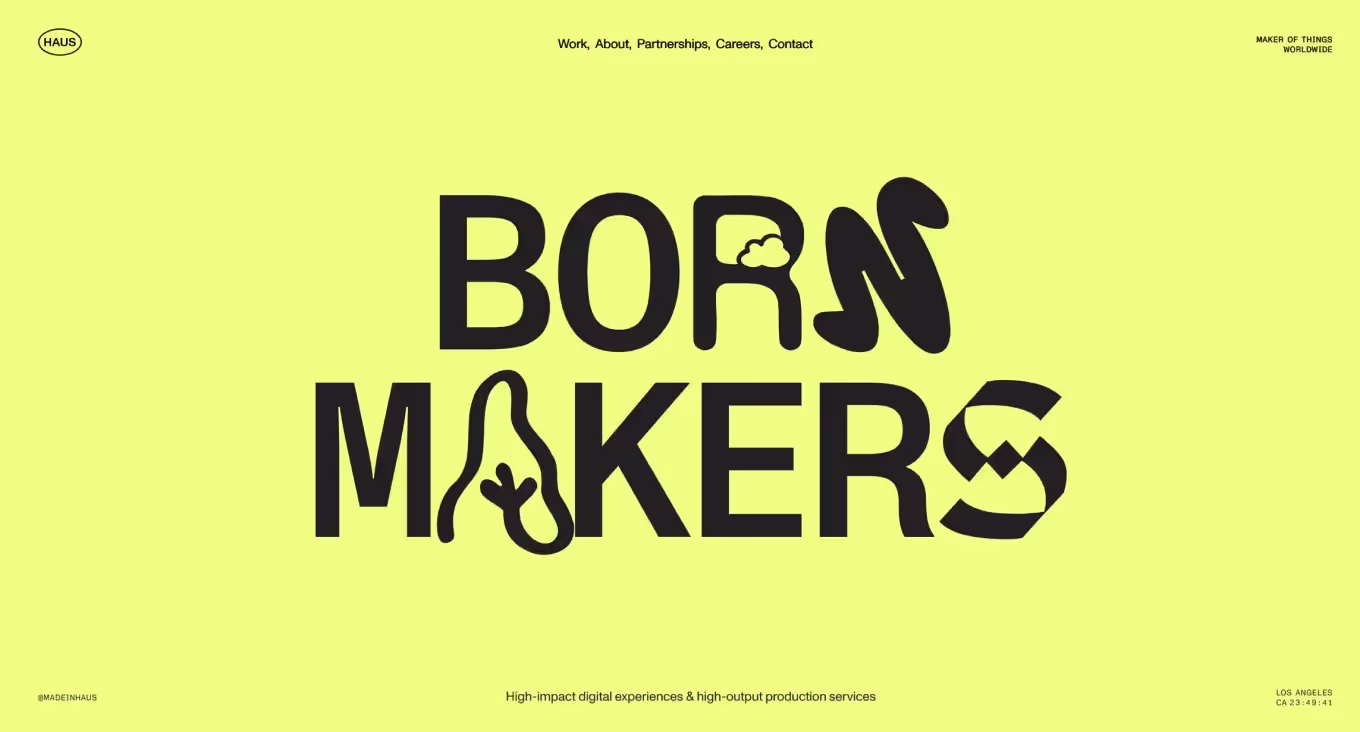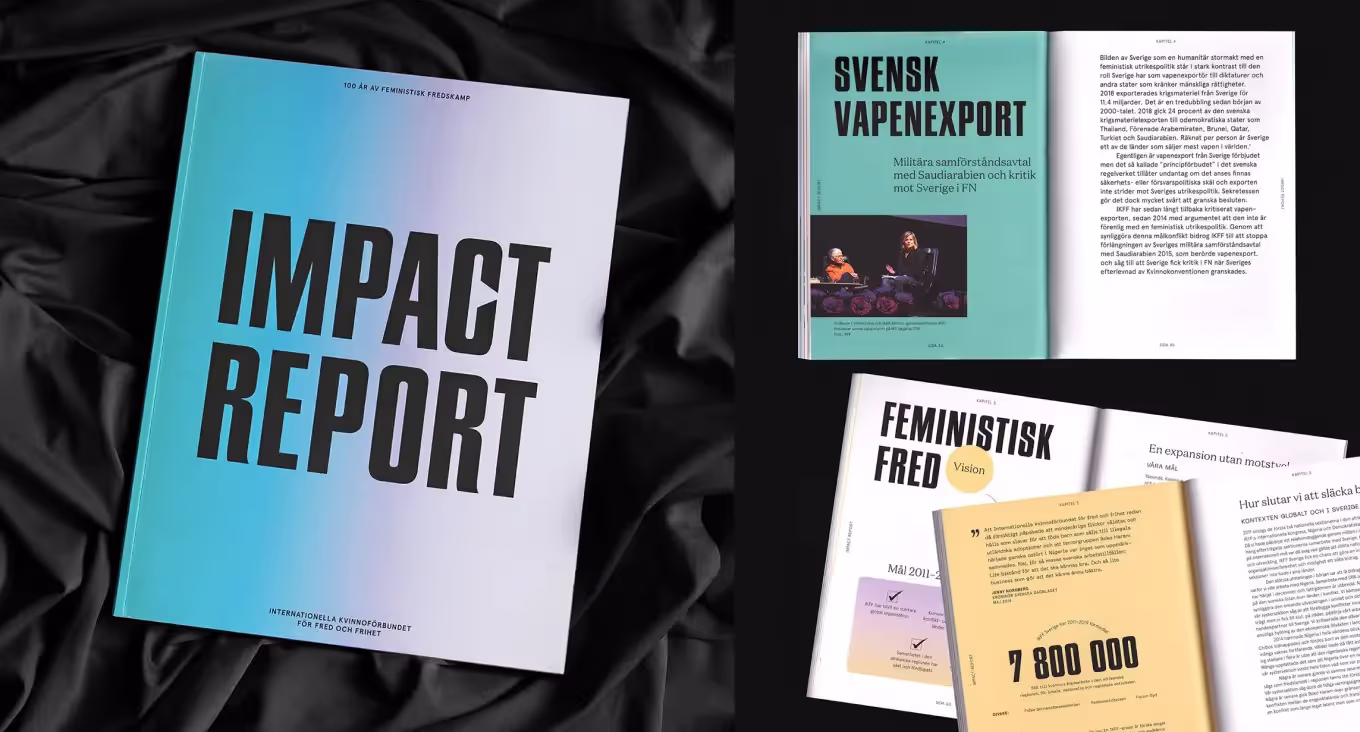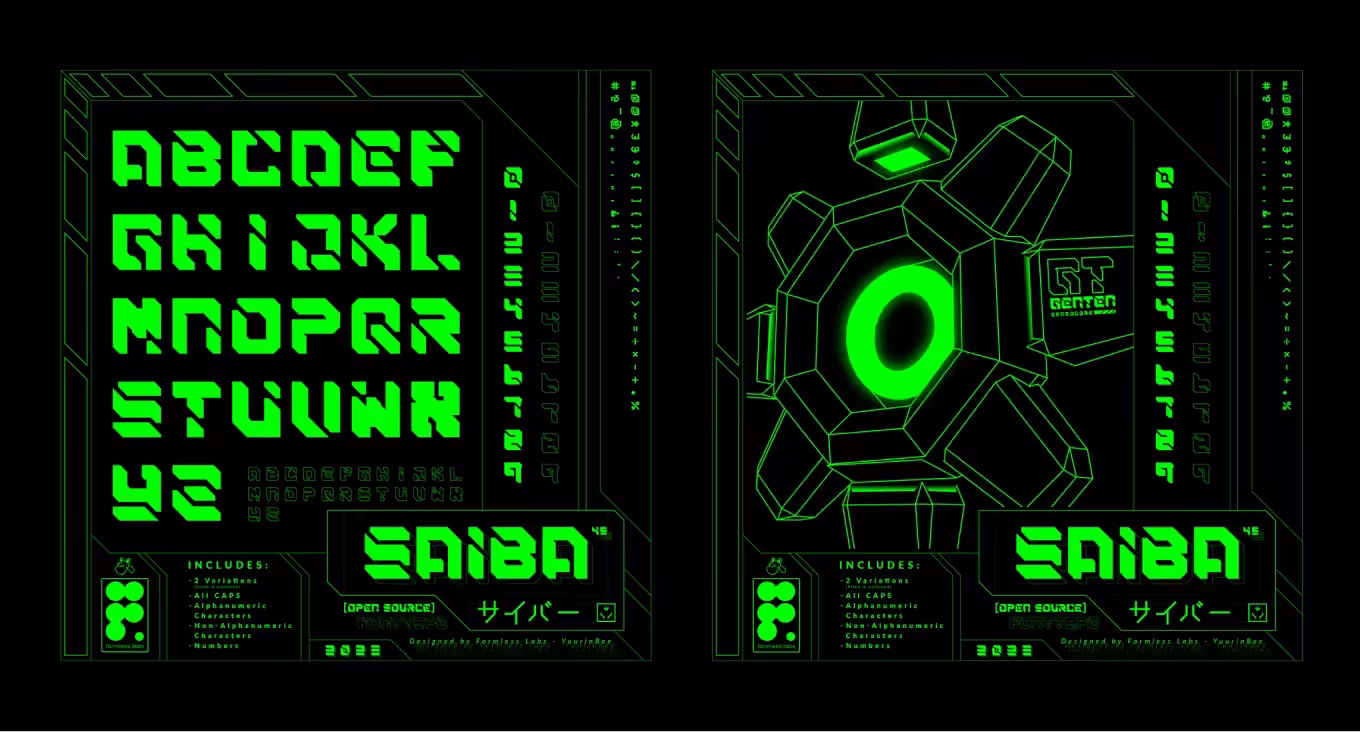
Как создать собственный шрифт?
Введение
Создание собственного шрифта требует много времени и усилий, но тем не менее все больше дизайнеров хотят попробовать себя в этой роли.
Создать шрифт — это не просто технически отрисовать литеры и символы, необходимо знание и понимание типографики, композиции, а также психологии восприятия.
В этом лонгриде мы расскажем вам, с чего начать создание собственного шрифта, что необходимо изучить и какие программы можно использовать, если это ваш первый шрифт.
Зачем вам создавать шрифт?
Давайте для начала рассмотрим причины, по которым дизайнеры создают новые шрифты, хотя, казалось бы, их итак существует огромное количество.
Уникальность бренда
Визуальная идентичность — один из мощнейших инструментов дифференциации современных брендов. Именно собственный и особенный шрифт становится частью брендинга компании, помогает создать уникальный образ и связь с целевой аудиторией. Он отражает характер и ценности, специфику и историю.
Реализация концепции
Необычный шрифт поможет точнее передать не только идею, но и ощущения, атмосферу проекта. Вы сможете уйти от шаблонов, сложившихся ассоциаций и создать уникальный дизайн для конкретной целевой аудитории или специфической сферы.
Развитие дизайнера
А еще создание собственного шрифта может стать творческим вызовом, который поможет глубоко погрузиться в типографику и выйти на новый уровень в работе. По сути вы расширяете границы своего творческого потенциала и выражаете индивидуальность в каждой составляющей работы, даже в запятой.
Этап 1. Определение цели и характера шрифта
Перед тем как приступить к созданию шрифта, нужно определить его характер и назначение. Это поможет создать такой шрифт, который будет отвечать необходимым требованиям, чтобы эффективно решать задачи.
Для чего вам нужен шрифт?
Веб-сайт. Высокочитабельный шрифт, который будет хорошо смотреться на экранах различного размера и гармонично вписываться в дизайн.
Бренд. Шрифт отражает ценности и идентичность бренда, создавет узнаваемый и запоминающийся образ.
Приложения. Удобный и легковоспринимаемый в интерфейсе шрифт, который хорошо читается с маленького экрана.
Печатные материалы. Шрифт удобен для использования в разных форматах печати: газеты, книги, журналы и пр., подходит для большого массива текста и смотрится гармонично с дизайном публикаций.
Упаковка
Какой должен быть характер у шрифта?
01
Современный
Минималистичный и чистый без лишних элементов, ясный и функциональный.
02
Классический
Элегантный и более традиционный, выглядит утонченно и гармонично.
03
Дружелюбный
Мягкий, теплый и неформальный, создающий ощущение уюта и заботы.
04
Строгий
Официальный и серьезный, отличается от прочих лаконичностью дизайна и высокой четкостью.
05
Динамичный
Оригинальный, энергичный и яркий, примечателен своей нестандартностью.
На какую ЦА рассчитан шрифт?
01
Возраст
Молодая аудитория оценит динамичные и нестандартные шрифты, а вот для старшего поколения важнее читабельность шрифта.
02
Пол
Для женской аудитории дизайнеры выбирают элегантные и изящные шрифты, в то время как мужская аудитория предпочитает строгость и лаконичность.
03
Культура
Учитывайте культурные особенности своей будущей целевой аудитории, чтобы в результате шрифт выглядел уместно и воспринимался пользователями положительно.
04
Сфера
Если ваш проект связан с детьми, то шрифт будет игривым и необычным, а для более серьезной тематики, например, сайт медицинского учреждения, стоит сделать шрифт лаконичным и строгим.
Определите для себя данные характеристики, пропишите их и только потом переходите к созданию концепции и отрисовке эскизов.
Этап 2. Выбор типа шрифта
Антиквы или шрифты с засечками (классический, элегантный стиль)
У шрифтов на концах букв имеются характерные элементы — небольшие засечки. Такие шрифты добавляют тексту ощущение стабильности и достоверности.
Например: Times New Roman, Garamond, Baskerville, Didot, Bodoni.
Применение: Печатная продукция с большим объемом текстов: книги и журналы, официальные документы, классические логотипы.
Гротески или шрифты без засечек (современный и минималистичный стиль)
У этих шрифтов нет засечек, они более лаконичны и нейтральны в сравнении с антиквами. Отлично вписываются в актуальные минималистичные дизайны и добавляют тексту простоты и ясности.
Например: Arial, Helvetica, Roboto, Open Sans, Lato.
Использование: Веб-сайты и приложения, интерфейсы, заголовки, короткие и объемные тексты.
Декоративные шрифты
Это очень большая группа шрифтов, каждый из которых отличается нестандартной формой букв и разнообразными декоративными элементами. Это могут быть:
Заключение
Относитесь к созданию своего собственного шрифта не как к чисто техническому процессу, а как к новому вызову и творческому приключению. Изучайте историю типографики и основные принципы, вдохновляйтесь классическими шрифтами и новыми идеями, экспериментируйте с разнообразными стилями и формами и, главное, не торопитесь. Процесс создания шрифта может расширить ваш творческий потенциал, помочь приобрести новые навыки и просто доставить вам удовольствие.